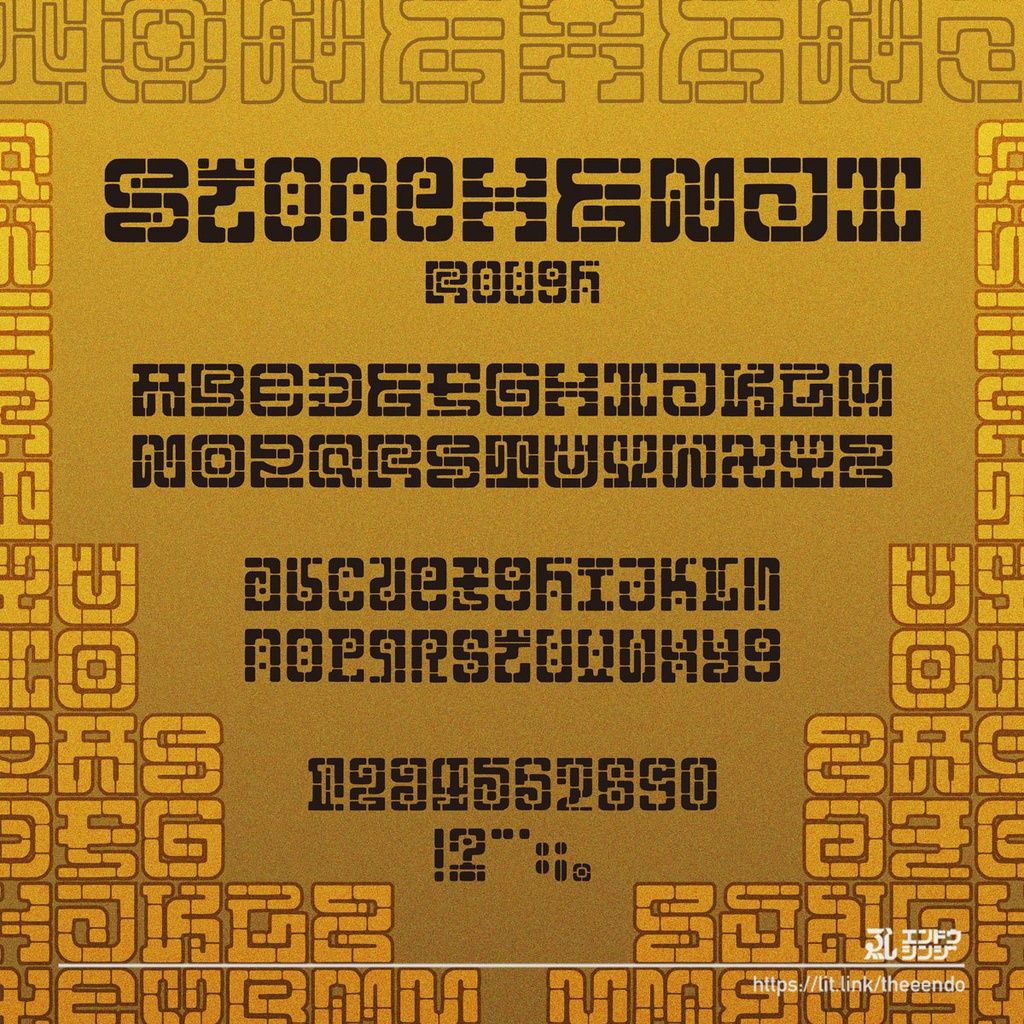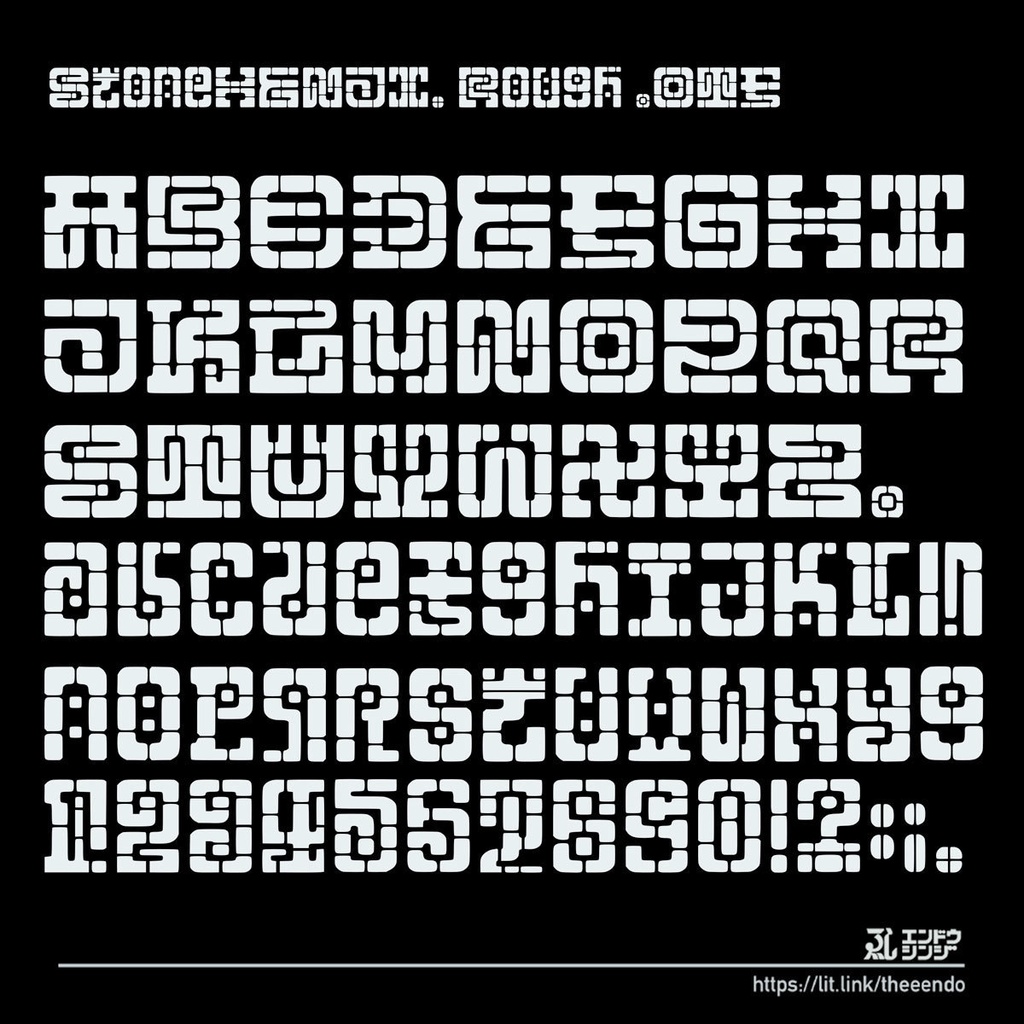
フォント「Stone HENJI_Rough (ストーンヘンジ_ラフ)」
『StoneHENJI_Rough (ストーンヘンジ_ラフ)』 OpenTypeフォント 古代文明の石に刻まれた文字をイメージした英文フォント。 ■収録文字 英数字・一部記号 ■ご利用に関して エンドウシンジの以下のアカウントをフォローしている方であれば、禁止事項に抵触しない範囲内で自由に使用することができます。商用利用も可です。フォローされていない方は個人利用の範囲での使用に留めて下さい。 ーーー以下いずれかフォローをお願いしますーーー X : https://x.com/mamezone Booth: https://theeendo.booth.pm/ Instagram : https://www.instagram.com/shin_thee_endo/ ■禁止事項 1. 本フォントを第三者に譲渡・貸与・配布・販売することはできません。 2. 本フォントを犯罪行為と見做されるもの、誹謗・中傷目的で使用することはできません。 3. 本フォントを使用したロゴマーク等の商標登録・意匠登録することはできません。 4. 本フォントのデータを元に、新たな類似または同一フォントのデータを作成することはできません。 判断が難しい場合はお問い合わせください。 ■その他 ・本フォントに伴う技術的なサポートはいたしません。 ・本フォントを使用して発生したと思われる如何なる問題についても、Thee endo /エンドウシンジは責任を負わないものとします。 ・動作確認はMacのみで行っています ・本フォントの著作権その他一切の権利はThee endo /エンドウシンジ に帰属します。 ・上記に記載されていない条項に関しては、著作権法及び関連法規に従うものとします。 ・本フォントは将来予告なしにアップデート、配布終了する場合があります。 ■お問い合わせ先 mail: mame777@gmail.com X: @mamezone